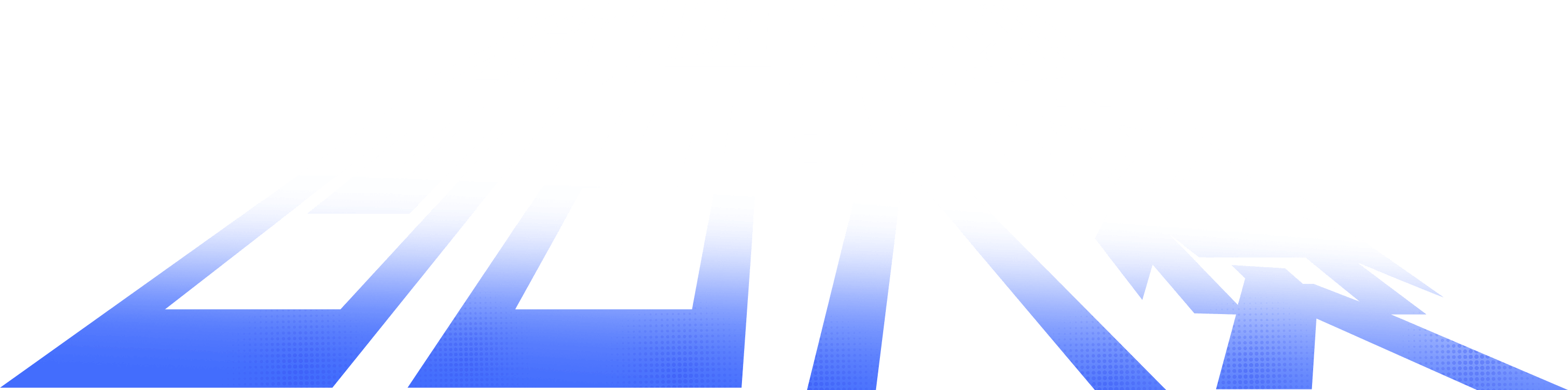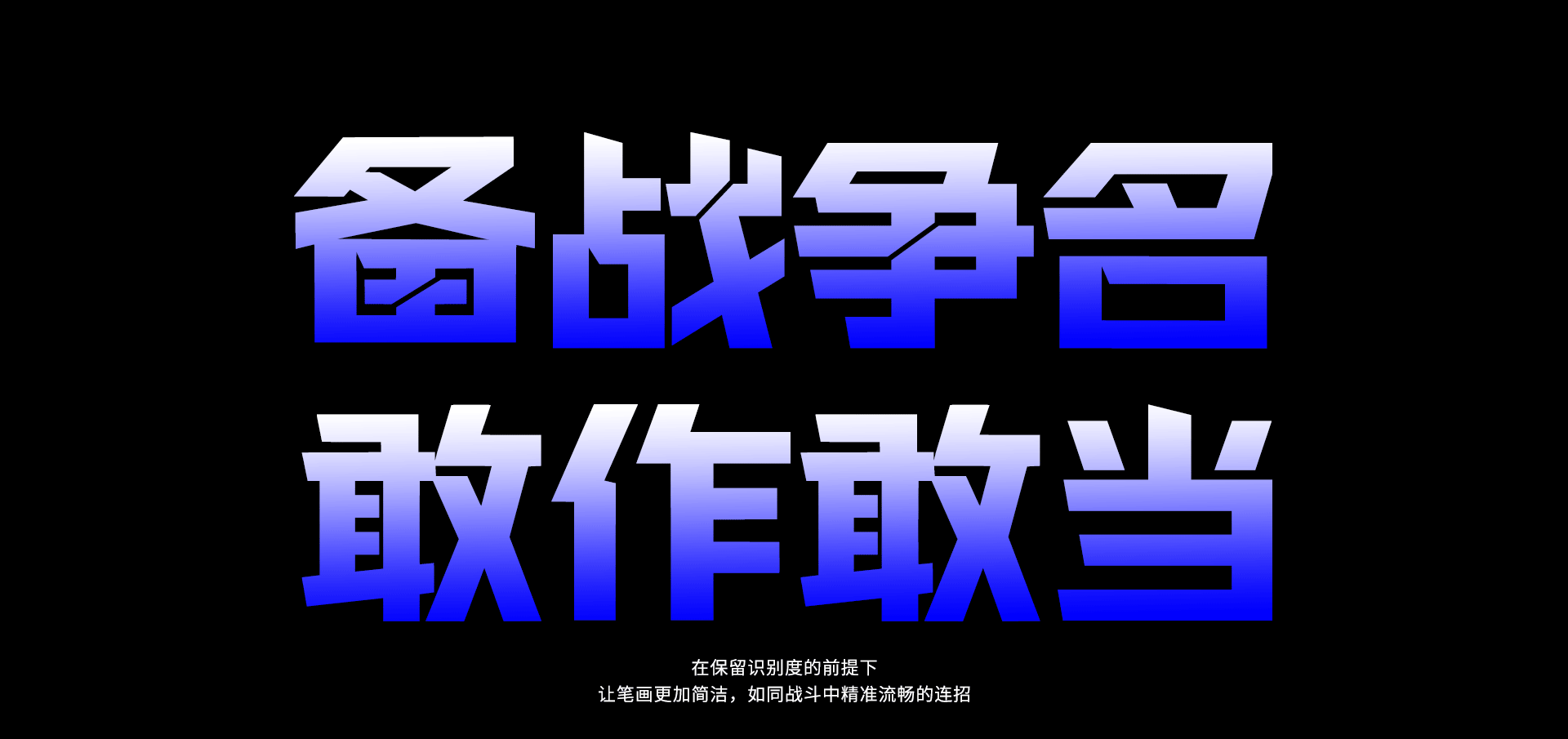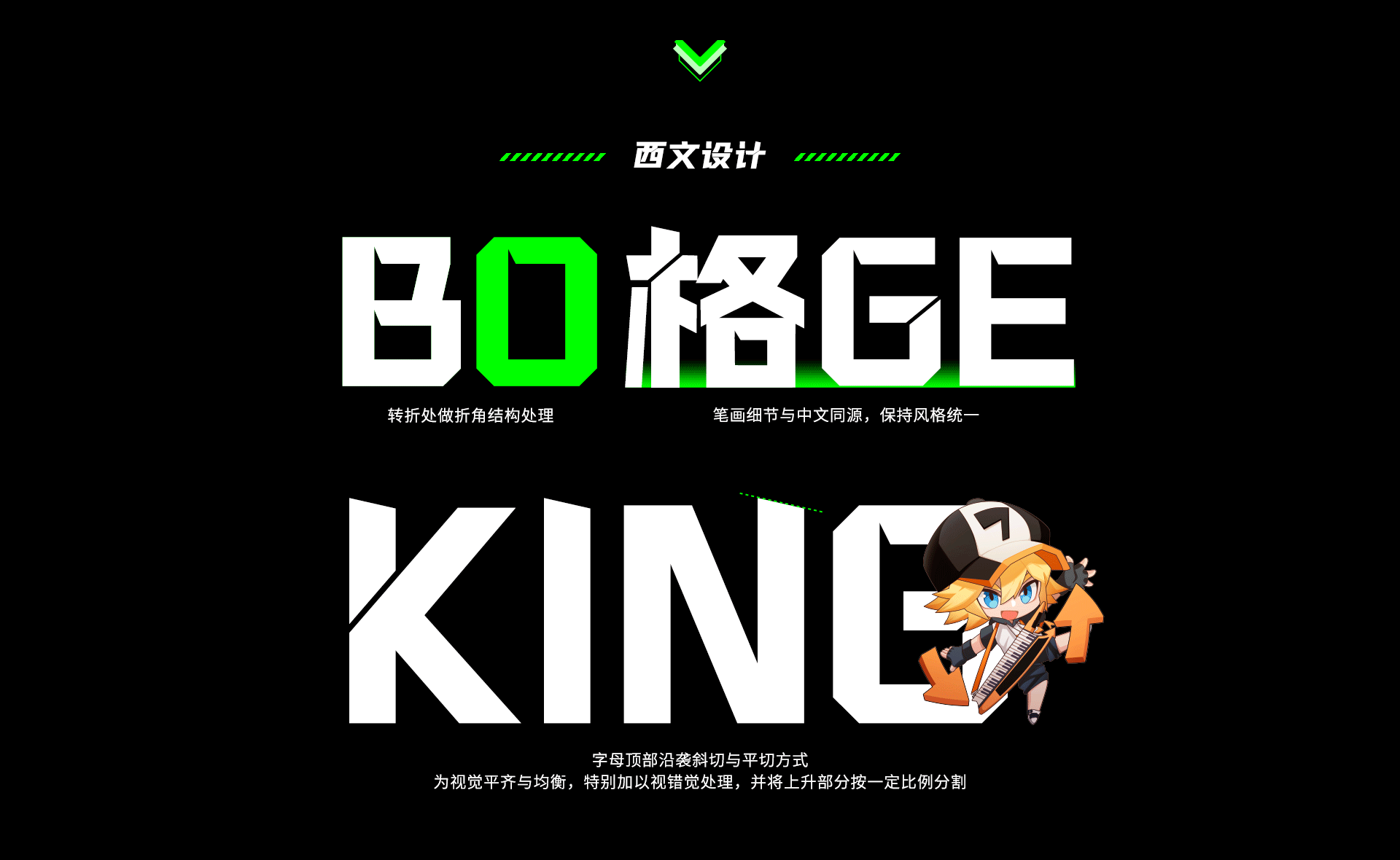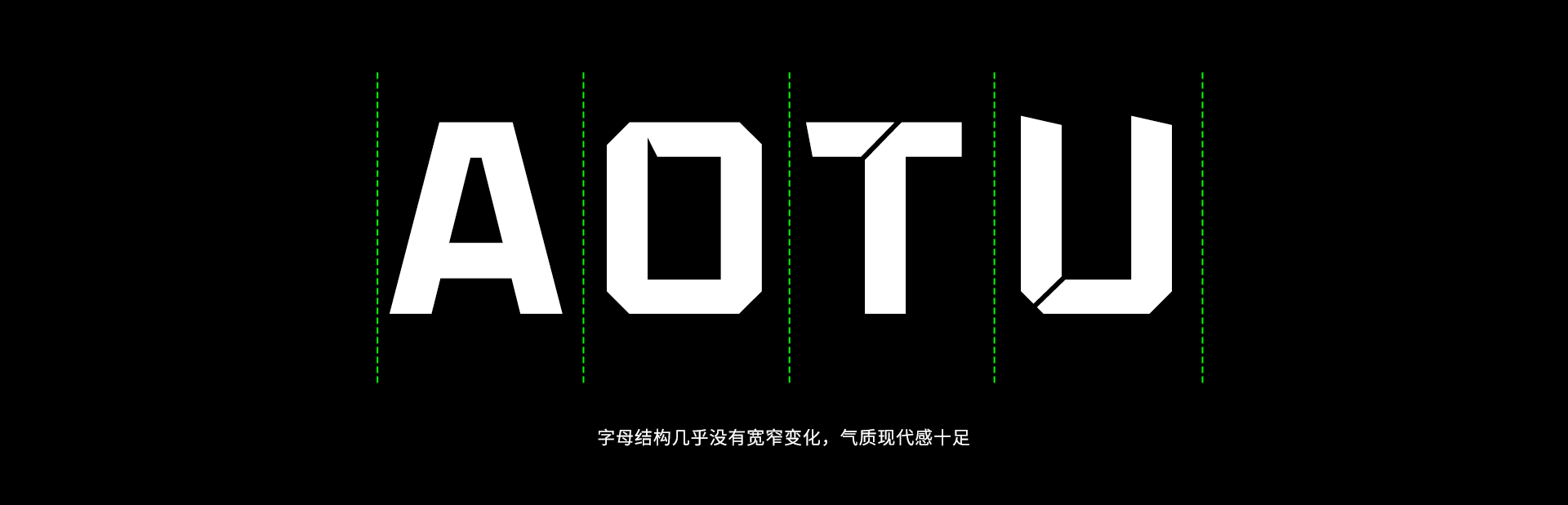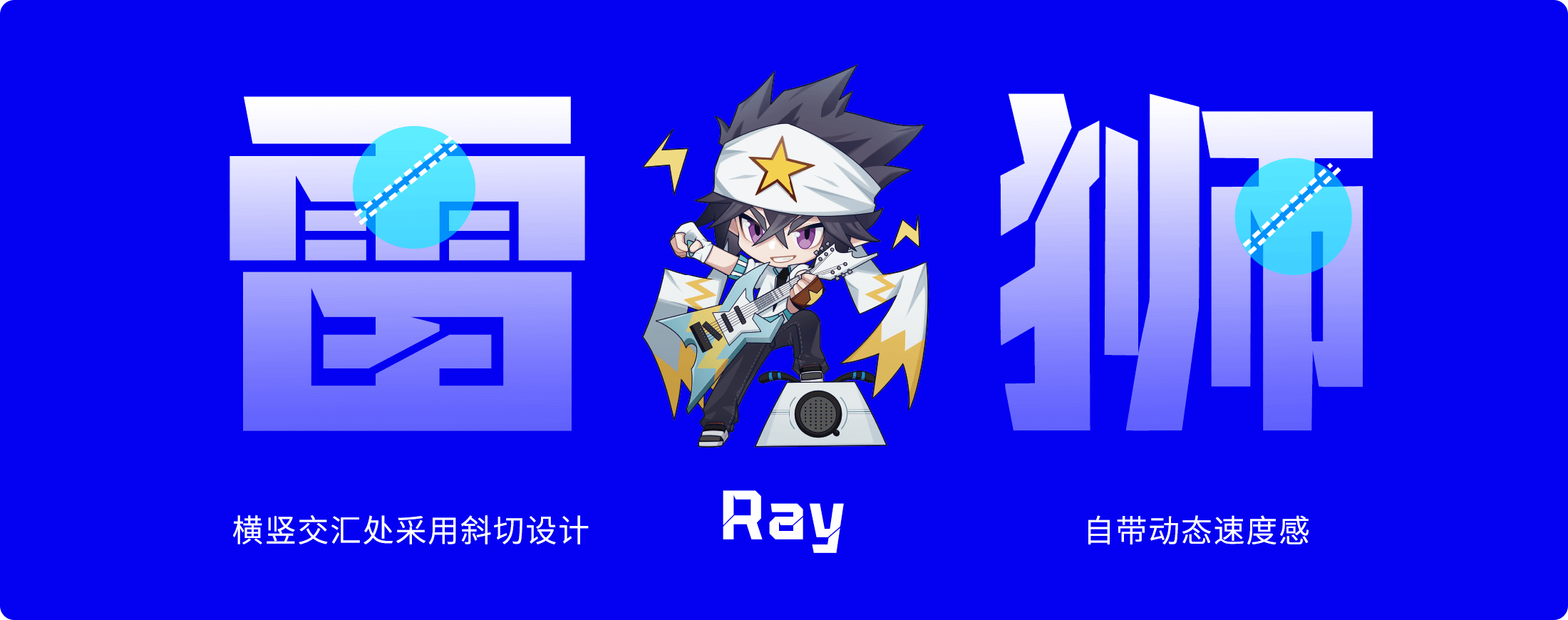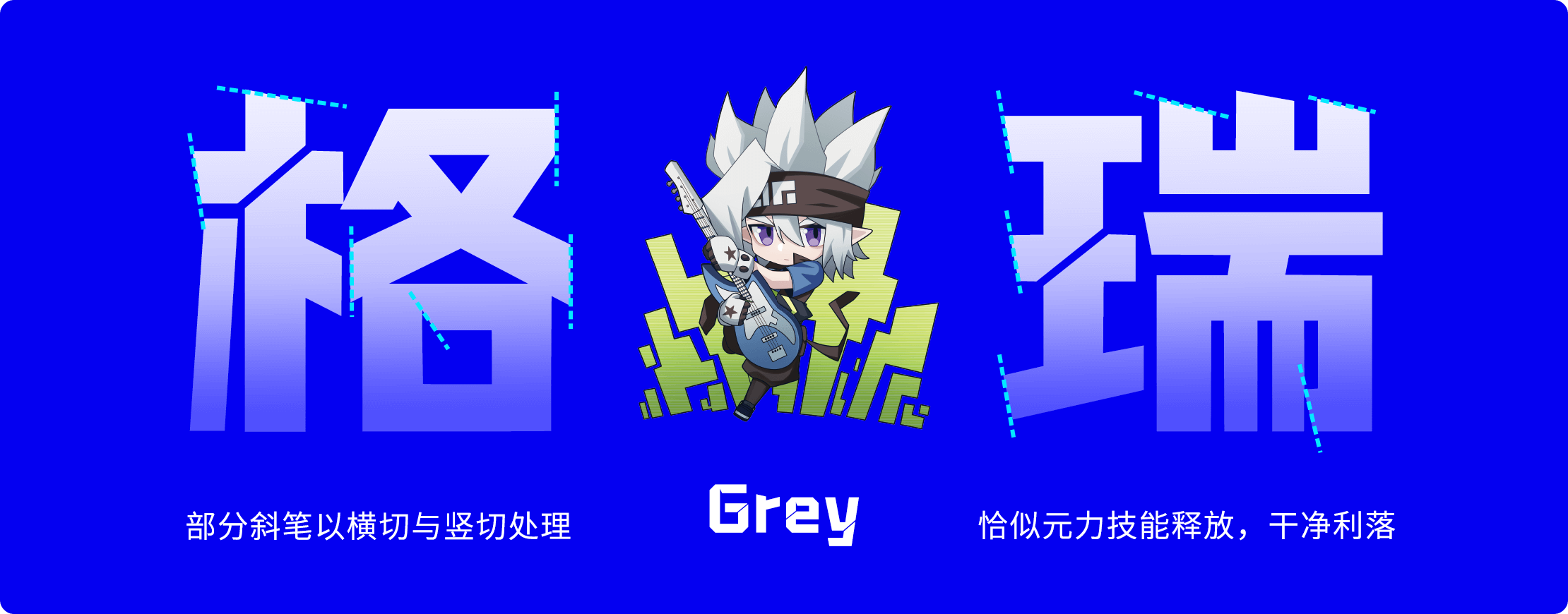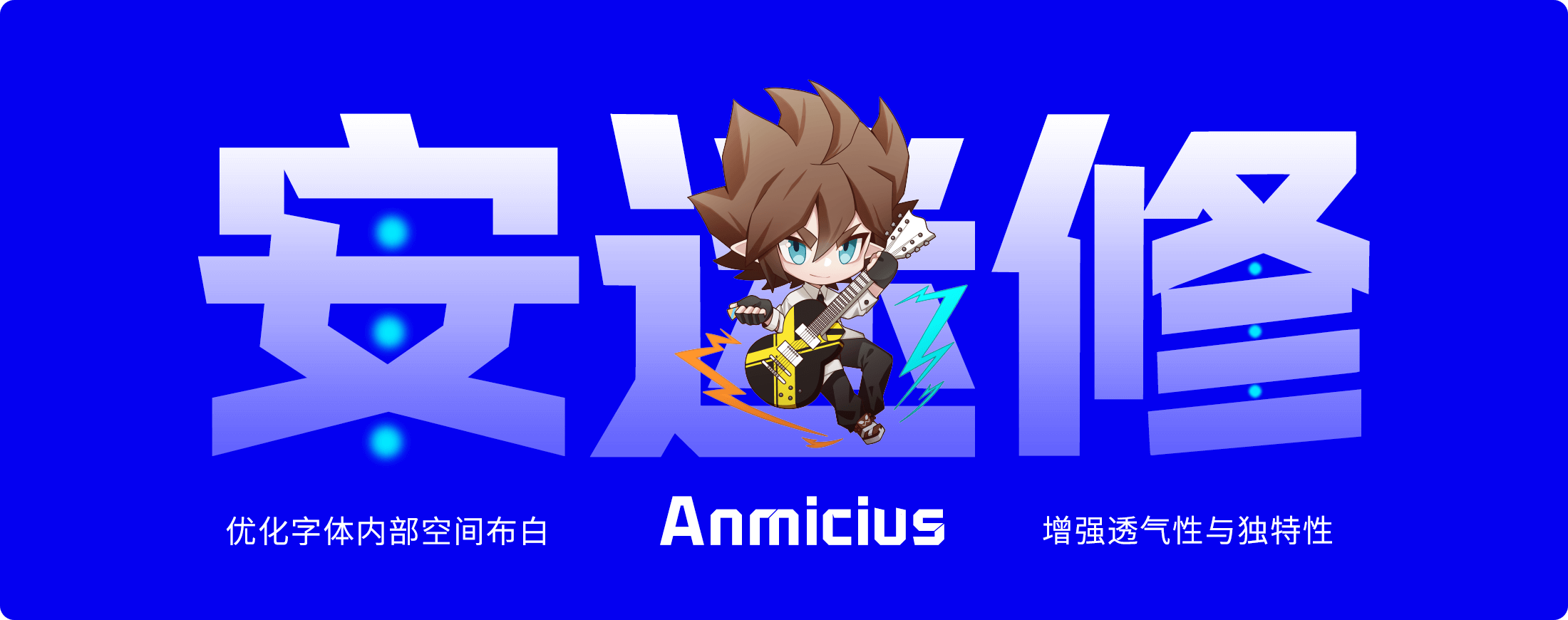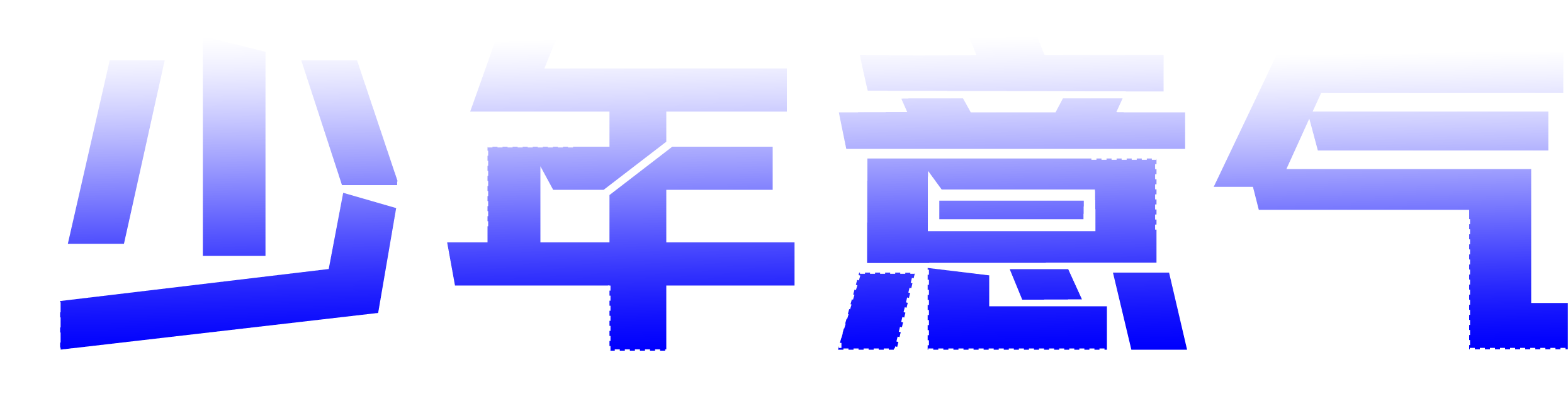
凹凸世界
基于对「凹凸世界」IP的美术风格、粉丝文化、用字场景等的深入调研
字魂以IP设定中已有的视觉锤——凹凸世界西文为灵感源泉
将几何机械感与战斗张力融入字体架构
让字形本身,成为凹凸美学的视觉延伸
热血战斗
酷炫潮流
个性张扬
视觉冲击
强烈的科技感与未来风格
IP世界观设定中的凹凸文
保留其美学特色的定制字体
硬核的整体气质
字型方正偏扁,沉稳大气
如参赛者伫立赛场
沉着中暗藏爆发力
以直线、直角为核心造型语言
笔画硬朗锐利,无圆润曲线
充满机械感与力量
个性化的几何切割
极简化与连笔处理
深入知名国漫ip《凹凸世界》别具一格的设计美学,字魂从IP独特的Low Poly画风与热血气质中汲取灵感,为其打造专属定制字体,助力IP宇宙的视觉统一化。
凹凸风格 showtime!
从官方宣传到玩家阵地,从游戏界面到衍生周边
凹凸世界」 高度契合IP生态的每一个角落
让美学统一,也让热血延续
定制设计充分考量了在不同应用场景、业务版块及媒介载体上的使用
使字体在保持个性识别的同时,具备高度的清晰度与可读性
展现出美观而稳定的应用效果
应用场景:官网界面及运营素材、社交媒体图文设计、线下宣传物料制作
应用场景:游戏UI界面、游戏系统文案、剧情相关文字
应用场景:周边产品及包装设计、电商页面、零售终端及卖场陈列、线下展会物料呈现